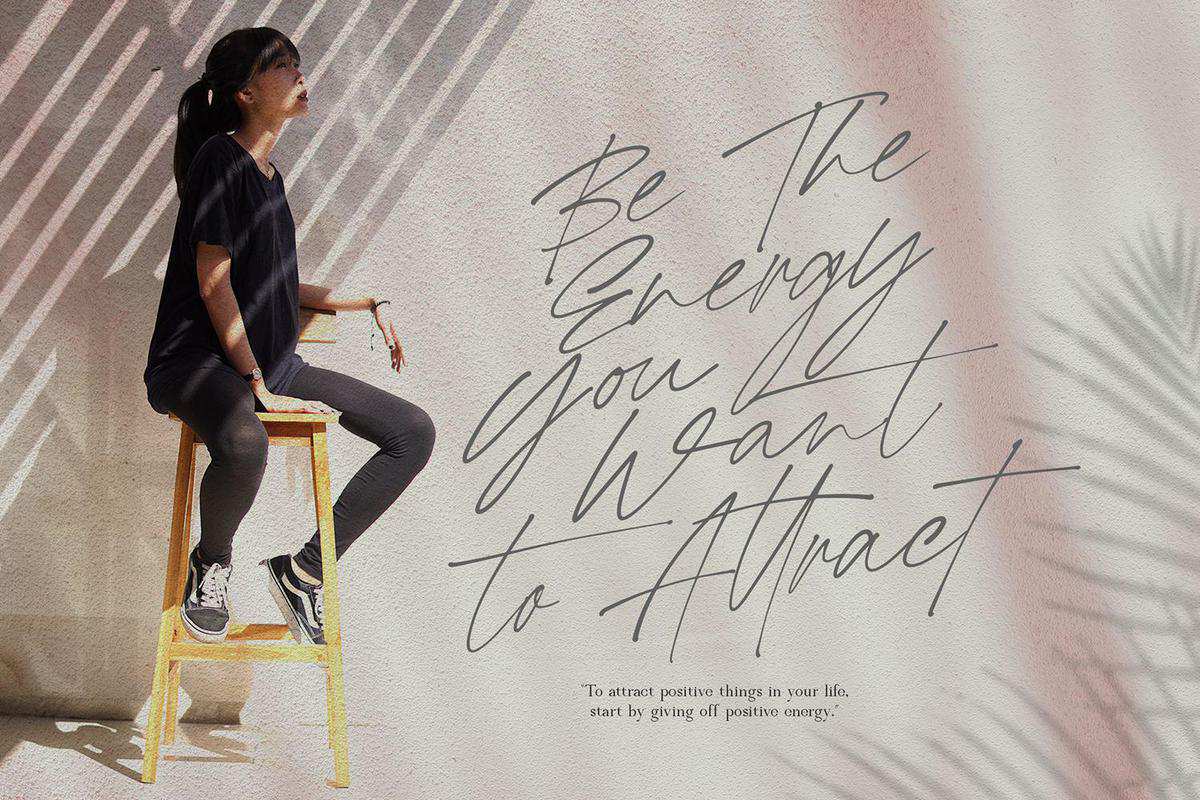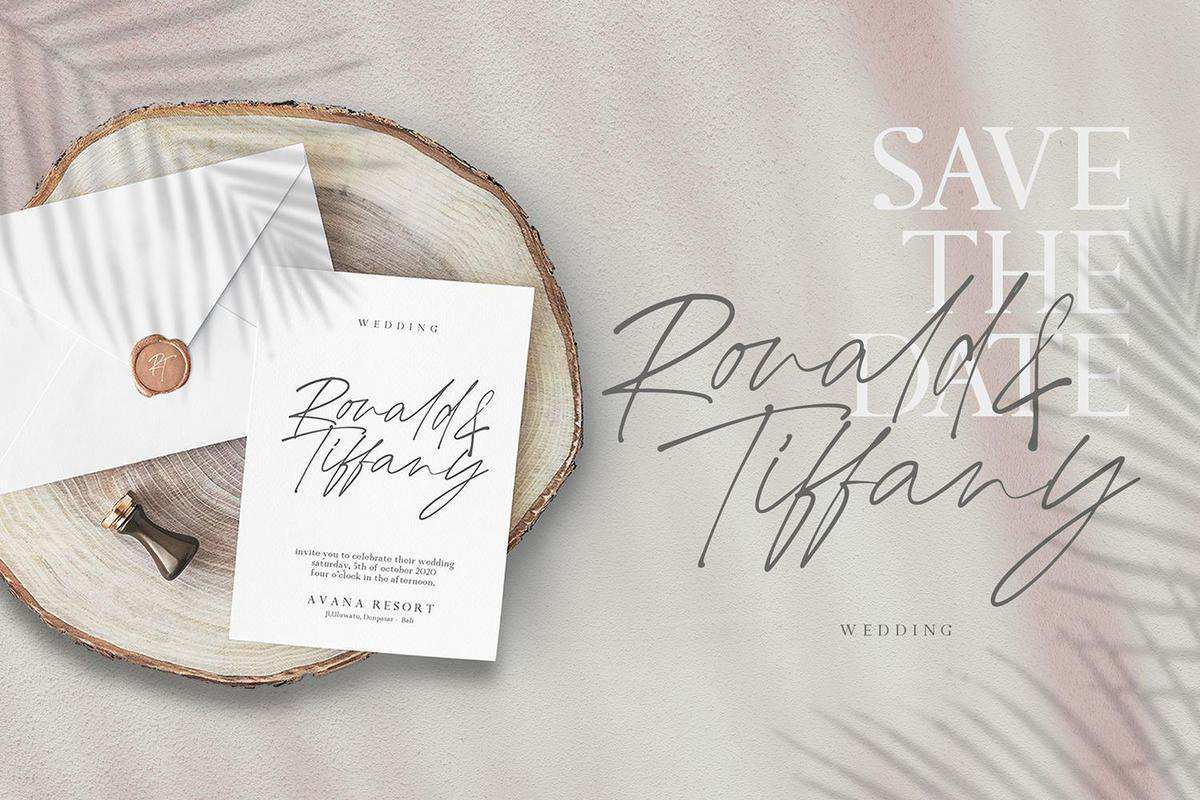
现代卡利马特采用自然和刮痕设计,使现代卡利马特适合用于增强您的设计。现代卡利马特采用2种样式,包括脚本和系列字体以及完美的打印字体,KalClimatascripts具有独特的自然纹理,给您的设计留下了深刻的印象和自然流,并且KalClimatascripts能够使KalClimatascripts看起来更漂亮,更适合于在单元中描述。现代KalClimata还可以与装饰现代KalClimata的非常粗糙的替代性特征相比较。现代KalClimata的完美选择是用于后期设计、签名、徽标、报价、专辑封面、名片、产品设计和许多其他设计项目。使用时,现代卡利玛塔位于手臂上。我们使这款字体看起来优雅、优雅、易于阅读、时尚、易于记忆,并且简单。现代卡利材料采用自然和刮痕设计,使现代卡利材料适合用于增强设计。现代卡利材料采用2种样式,包括脚本和系列字体,具有完美的印刷字体,KalClimatascripts具有独特的自然纹理,给您的设计留下了深刻的印象和自然流,并且KalClimatascripts能够使KalClimatascripts看起来更漂亮,更适合于在单元中描述。现代KalClimata还可以与装饰现代KalClimata的非常粗糙的替代性特征相比较。现代KalClimata的完美选择是用于后期设计、签名、徽标、报价、相册封面、名片、产品设计和其他许多设计项目。使用时,现代卡利玛塔会让它看起来优雅、优雅、易读、时尚、易记且简单。